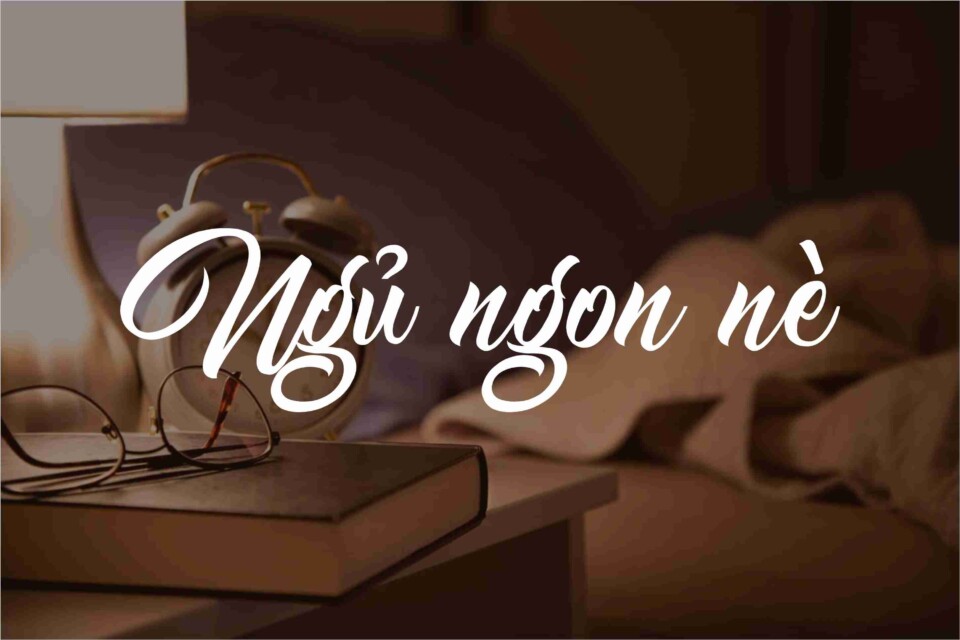
Font Việt hóa VN Nightfall Script
Giới thiệu về Font Việt hóa VN Nightfall Script trong thiết kế đồ họa
Trong thế giới sáng tạo, việc lựa chọn một bộ Font Miễn Phí chất lượng đóng vai trò then chốt để tạo nên hồn cốt cho tác phẩm. Font Việt hóa VN Nightfall Script nổi lên như một hiện tượng trong cộng đồng designer Việt Nam nhờ sự kết hợp hoàn hảo giữa nét cổ điển và hơi thở hiện đại. Đây là một phông chữ dạng script với những đường nét uyển chuyển, mềm mại nhưng vẫn giữ được cấu trúc chắc chắn. Khi sử dụng Font Việt hóa VN Nightfall Script, người dùng sẽ cảm nhận được sự tinh tế trong từng nét chữ, giúp các bản thiết kế trở nên có chiều sâu và giàu cảm xúc hơn bao giờ hết. Bộ font này đặc biệt phù hợp với những người đang tìm kiếm sự phá cách nhưng vẫn đảm bảo tính thẩm mỹ cao trong trình bày văn bản.
Đặc điểm nổi bật của Font Việt hóa VN Nightfall Script
Điều làm nên sự khác biệt của Font Việt hóa VN Nightfall Script chính là hệ thống ký tự được chăm chút tỉ mỉ. Các dấu tiếng Việt đã được tối ưu hóa để không bị chồng lấn hay làm mất đi vẻ đẹp nguyên bản của thiết kế gốc. Phông chữ này sở hữu các đường nối tự nhiên giữa các con chữ, tạo cảm giác như đang được viết tay bởi một nghệ nhân thư pháp thực thụ. Với độ tương phản nhẹ nhàng giữa các nét thanh và nét đậm, nó tạo ra một nhịp điệu thị giác lôi cuốn, giúp người xem dễ dàng tiếp nhận thông tin mà không cảm thấy mỏi mắt hay khó chịu.
Ứng dụng đa dạng của bộ Font Việt hóa VN Nightfall Script
Khả năng ứng dụng của Font Việt hóa VN Nightfall Script là cực kỳ rộng lớn, từ các dự án cá nhân đến chuyên nghiệp. Trong lĩnh vực thiết kế thiệp mời, đặc biệt là thiệp cưới, bộ font này mang đến sự sang trọng và lãng mạn khó có thể thay thế. Ngoài ra, các nhãn hàng thời trang hay mỹ phẩm cũng thường xuyên sử dụng phông chữ này để làm logo hoặc bao bì sản phẩm nhằm khẳng định phong cách quý phái. Đối với học sinh và giáo viên, phông chữ này có thể dùng để trang trí các bài thuyết trình, làm bìa báo tường hoặc thiệp chúc mừng thầy cô, giúp nội dung trở nên sinh động và mang đậm dấu ấn cá nhân hơn.
Lưu ý khi sử dụng Font Việt hóa VN Nightfall Script cho người mới
Để đạt được hiệu quả thẩm mỹ tốt nhất, người dùng nên kết hợp Font Việt hóa VN Nightfall Script với các phông chữ không chân (Sans Serif) đơn giản. Sự đối lập giữa nét chữ bay bổng của script và sự gọn gàng của sans serif sẽ giúp bố cục thiết kế trở nên cân bằng. Bạn cũng nên tránh viết hoa toàn bộ các từ khi sử dụng font script này vì sẽ làm giảm khả năng đọc và phá vỡ cấu trúc nghệ thuật của nó. Việc điều chỉnh khoảng cách dòng và khoảng cách chữ (kerning) một cách hợp lý cũng là yếu tố quan trọng để làm nổi bật vẻ đẹp của bộ chữ.